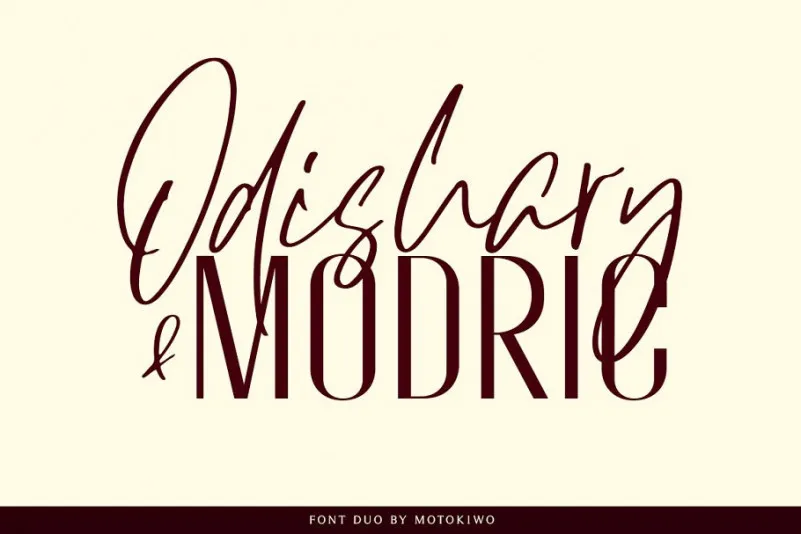
Odishary Script Font – Download Grátis
A Odishary Script Font é uma elegante alternativa para quem busca personalidade e sofisticação no seu design. Esta fonte está inspirada nas escritas manuscritas, oferecendo um estilo único e amigável ao mesmo tempo. Cada letra foi cuidadosamente desenhada com paixão para garantir que se combine bem com outros caracteres. É uma fonte de签字签名,适合作为品牌或标志项目、大标题文本和产品包装使用。设计者Motokiwo以其独特的精致手写体风格与连字符的结合而闻名。Odishary Script Font不仅仅是一个字体选择,它还带来了多语言字符,使设计师能够满足全球客户的不同需求。无论是在小型徽标还是大型广告牌上展示时,这款字体都能提供一种优雅且与众不同的视觉体验。